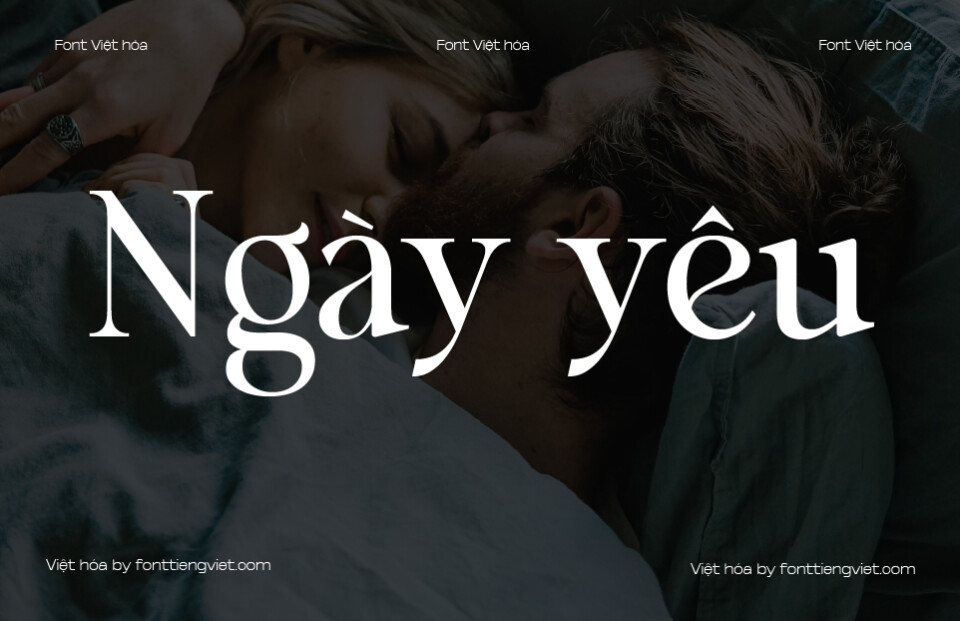
Font Việt hóa 1FTV VIP Malgio
Trong thế giới thiết kế đồ họa ngày nay, việc lựa chọn một bộ font chữ phù hợp đóng vai trò quyết định đến tính thẩm mỹ và thông điệp của sản phẩm. Một trong những cái tên đang thu hút sự chú ý của cộng đồng thiết kế chính là Font Việt hóa 1FTV VIP Malgio. Đây là bộ phông chữ mang phong cách hiện đại, thanh lịch và đặc biệt đã được tối ưu hóa hoàn toàn cho ngôn ngữ tiếng Việt. Nếu bạn đang tìm kiếm một Font Miễn Phí có khả năng ứng dụng linh hoạt từ làm slide bài giảng, thiết kế bìa sách đến các ấn phẩm truyền thông chuyên nghiệp, thì đây chính là sự lựa chọn không thể bỏ qua dành cho học sinh, sinh viên và các thầy cô giáo.
Đặc điểm nổi bật của bộ Font Việt hóa 1FTV VIP Malgio
Bộ font này nổi tiếng với các đường nét được trau chuốt tỉ mỉ, tạo nên sự cân bằng hoàn hảo giữa nét thanh và nét đậm. Điều này giúp văn bản trở nên dễ đọc ngay cả khi hiển thị ở kích thước nhỏ hoặc trên các thiết bị di động có độ phân giải thấp. Điểm cộng lớn nhất của phiên bản 1FTV VIP Malgio là hệ thống dấu tiếng Việt được thiết kế tinh tế, không bị lỗi dính dấu hay sai lệch khoảng cách vốn là nỗi ám ảnh của các nhà thiết kế Việt Nam.
Phong cách thiết kế hiện đại và tinh tế
Font Việt hóa 1FTV VIP Malgio sở hữu cấu trúc hình học hiện đại nhưng vẫn giữ được sự mềm mại cần thiết. Sự kết hợp này mang lại cảm giác chuyên nghiệp, rất phù hợp cho các bài thuyết trình tại trường học hoặc các dự án khởi nghiệp trẻ trung. Các ký tự được sắp xếp một cách khoa học, giúp bố cục trình bày trở nên thoáng đãng và bắt mắt hơn bao giờ hết.
Khả năng tương thích đa nền tảng
Ứng dụng thực tế của Font Việt hóa 1FTV VIP Malgio trong học tập
Đối với các bạn học sinh và giáo viên, việc sử dụng một bộ font đẹp như 1FTV VIP Malgio sẽ giúp các bài giảng và báo cáo trở nên sinh động hơn. Thay vì sử dụng những phông chữ mặc định khô khan, bộ font này thổi một làn gió mới vào các trang giáo án điện tử, giúp học sinh dễ dàng tiếp thu kiến thức và tạo ấn tượng tốt với người xem.
Thiết kế slide và bài giảng điện tử
Khi trình chiếu trên màn hình lớn, độ tương phản của Font Việt hóa 1FTV VIP Malgio giúp chữ viết rõ ràng từ mọi góc nhìn trong lớp học. Các tiêu đề chính sẽ trở nên nổi bật, giúp định hướng nội dung bài học một cách mạch lạc. Đây là yếu tố then chốt để xây dựng một môi trường giáo dục trực quan và hiện đại hơn.
Làm thiệp mời và poster sự kiện trường học
Trong các dịp lễ hội hay sự kiện ngoại khóa, bộ font này là trợ thủ đắc lực để tạo ra những tấm thiệp mời hay poster mang phong cách trẻ trung. Sự đa dạng trong cách thể hiện giúp bạn tự do biến hóa phong cách từ trang trọng đến gần gũi, đáp ứng mọi yêu cầu khắt khe nhất của các dự án sáng tạo cá nhân.
Kết luận về giá trị của Font Việt hóa 1FTV VIP Malgio